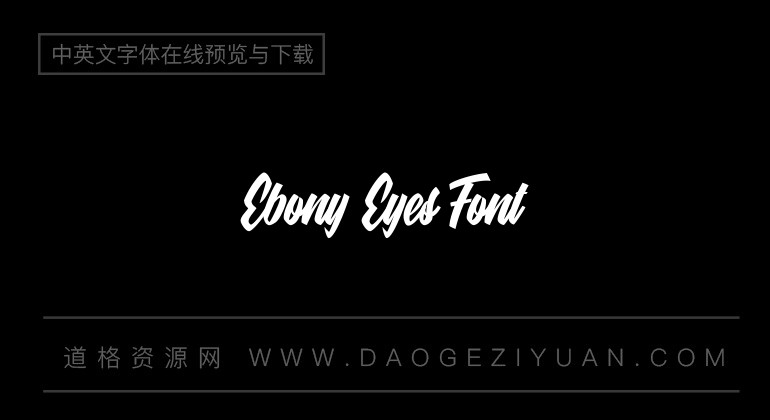
Ebony Eyes Font
Ebony Eyes 是一种手写风格的字体,具有优美的草书风格。它的特点是字母之间的连笔非常流畅,且字母具有一定的倾斜度,使得整个字体看起来非常自然而流畅。 这种字体适合用于设计手写风格的海报、宣传单、字幕、标语等,能够营造出一种温馨、亲切的感觉。同时,它也非常适合用于个人博客、名片、婚礼邀请函等场合。 Ebony Eyes 字体具有多种字重,包括 Regular、Bold、Italic、Bold Italic 等,能够满足不同场合的需求。此外,它还支持多种语言,包括英语、法语、西班牙语、意大利语等,非常方便使用。 总之,Ebony Eyes 字体是一种非常优美的手写风格字体,适合用于多种场合,无论是商业设计还是个人创作,都能够为您的作品增添独特的魅力。
Ebony Eyes Font是一款非常不错的手写艺术字体,具有很好的视觉感,适合于文化类的宣传设计、商业类品牌的广告和产品包装设计以及个性化文字排版等较多场景。